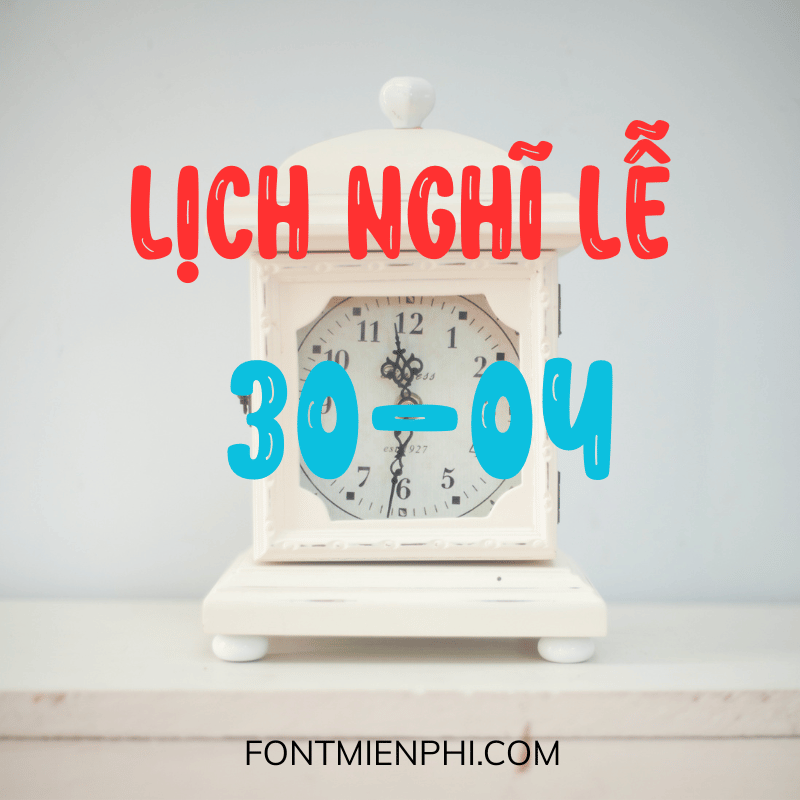
Font Việt hóa FMP Spooky Misteri
Font Việt hóa FMP Spooky Misteri  – Phong Cách Ma Mị, Độc Đáo
Font Việt hóa FMP Spooky Misteri là bộ font chữ nghệ thuật mang phong cách bí ẩn, ma mị, phù hợp cho các thiết kế Halloween, truyện kinh dị, poster phim hoặc dự án nghệ thuật đậm chất huyền bí. Với nét chữ uốn lượn, góc cạnh kết hợp hiệu ứng rùng rợn, font chữ này giúp tạo điểm nhấn ấn tượng, thu hút người xem ngay từ cái nhìn đầu tiên.
Đặc điểm nổi bật của  Font Việt hóa FMP Spooky Misteri :
• Thiết kế độc đáo: Nét chữ ma quái, phù hợp với chủ đề kinh dị, bí ẩn.
• Hỗ trợ Tiếng Việt: Đầy đủ dấu, tương thích với mọi phần mềm thiết kế.
• Đa dạng ứng dụng: Dùng cho Photoshop, Illustrator, game, video, in ấn…
• Chất lượng cao: Font sắc nét, dễ đọc nhưng vẫn giữ được phong cách riêng.
Font Việt hóa FMP Spooky Misteri